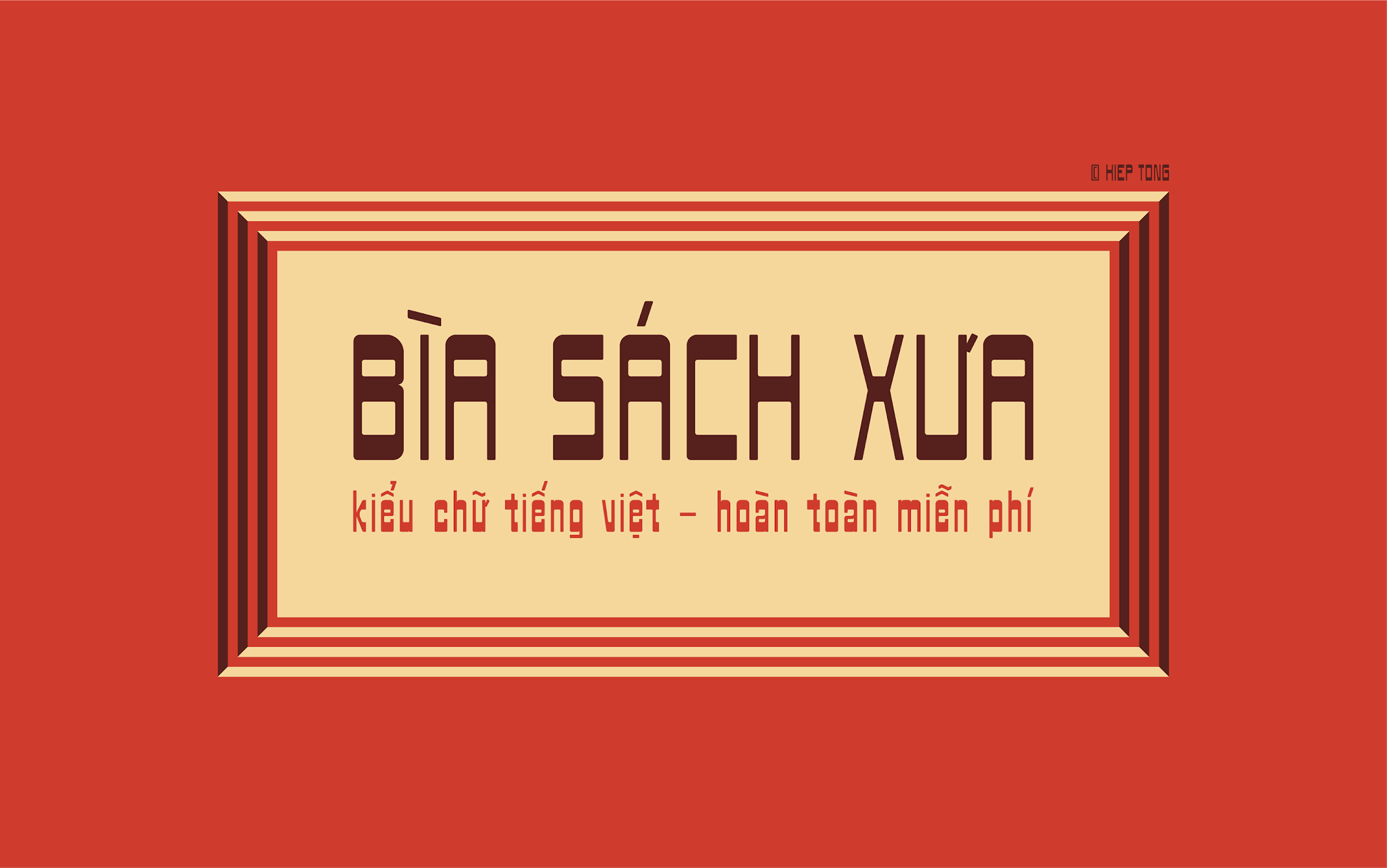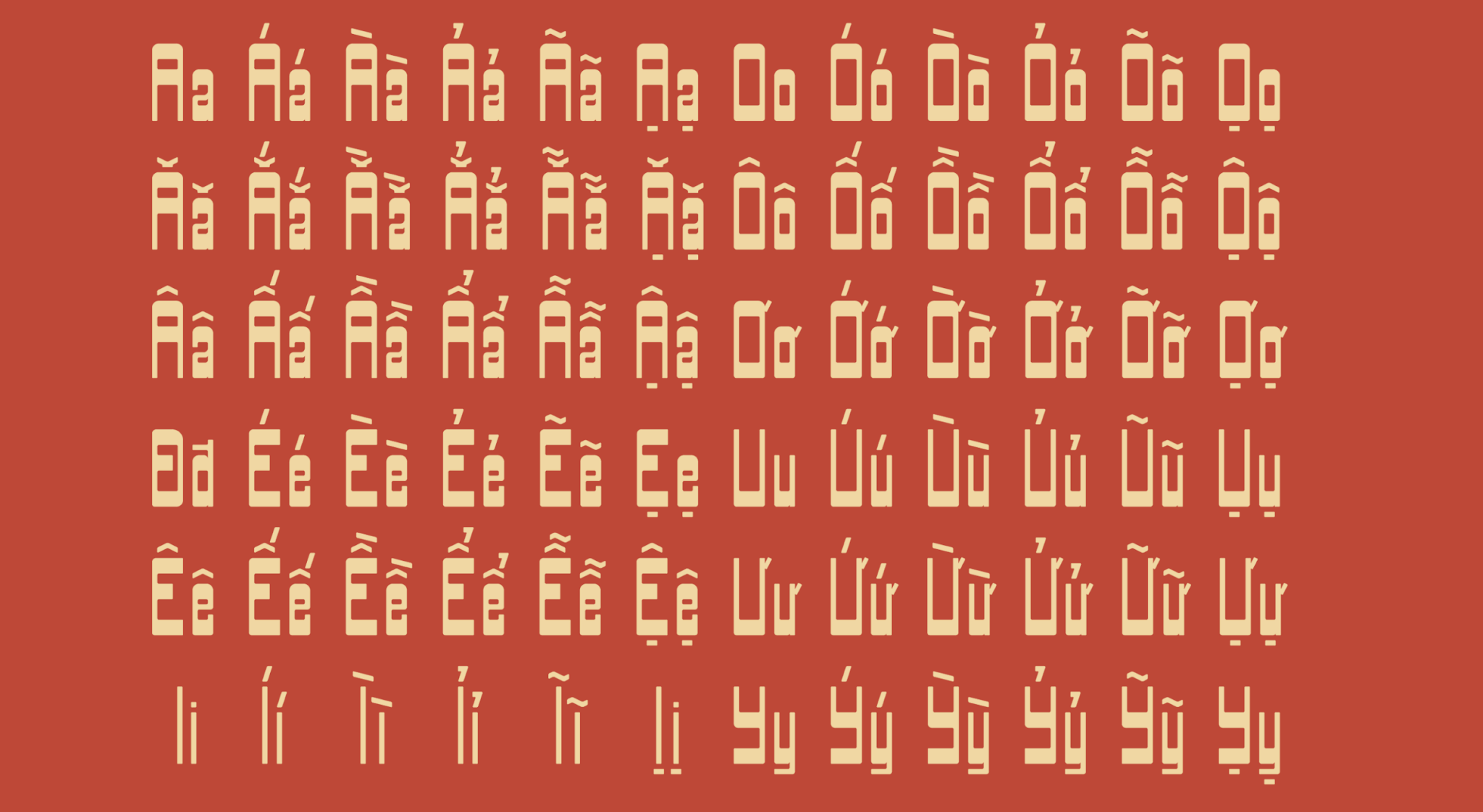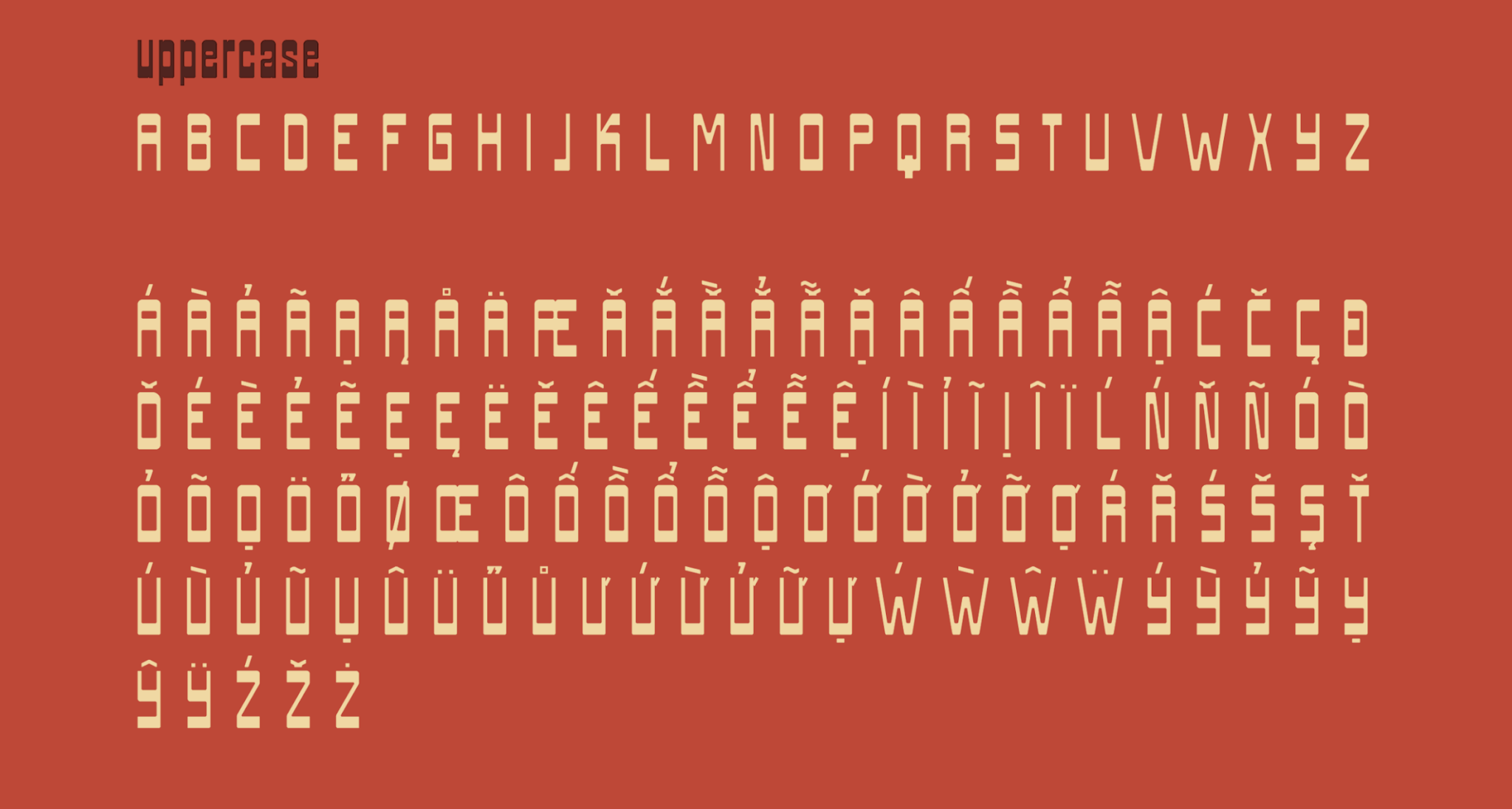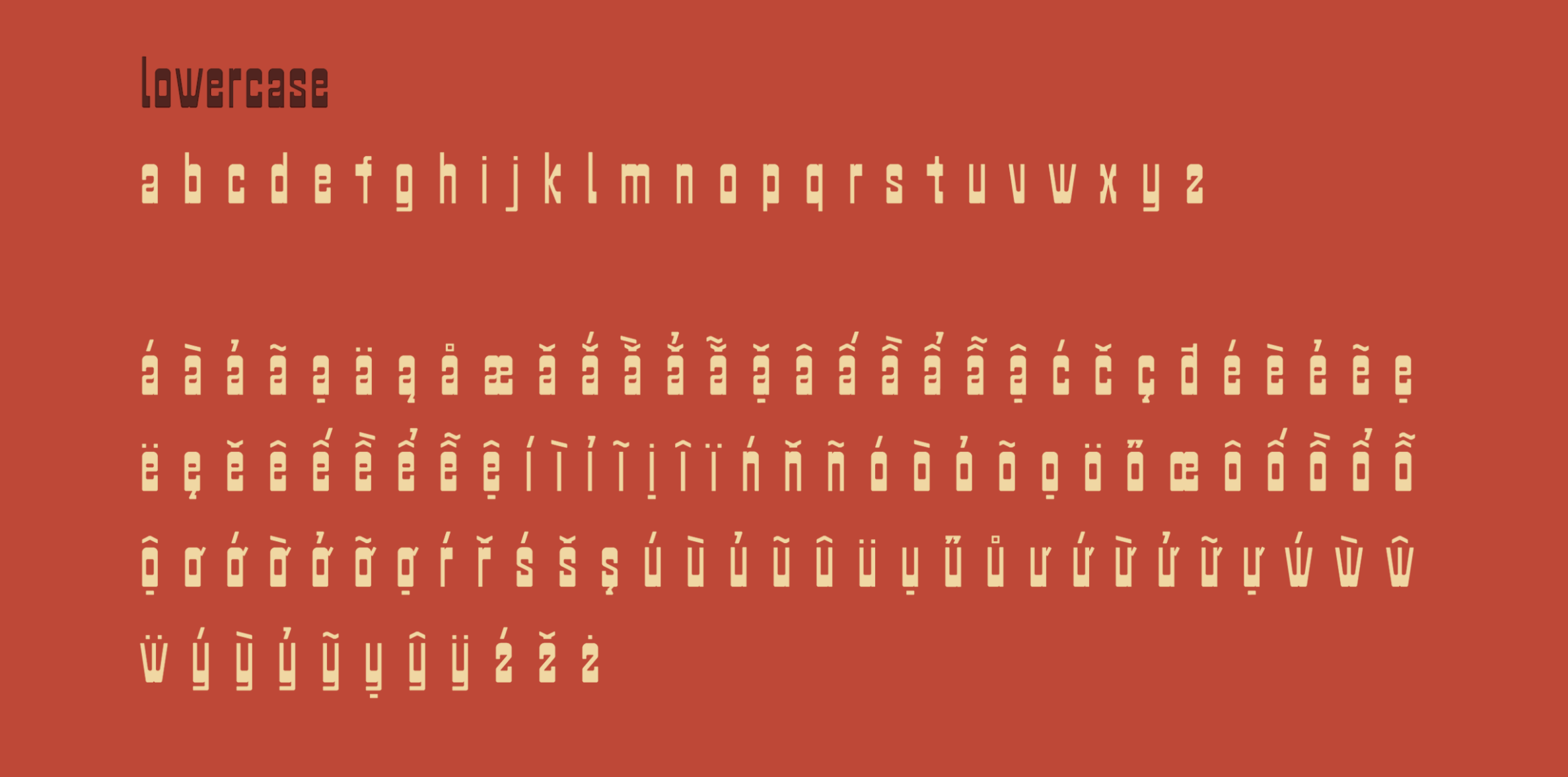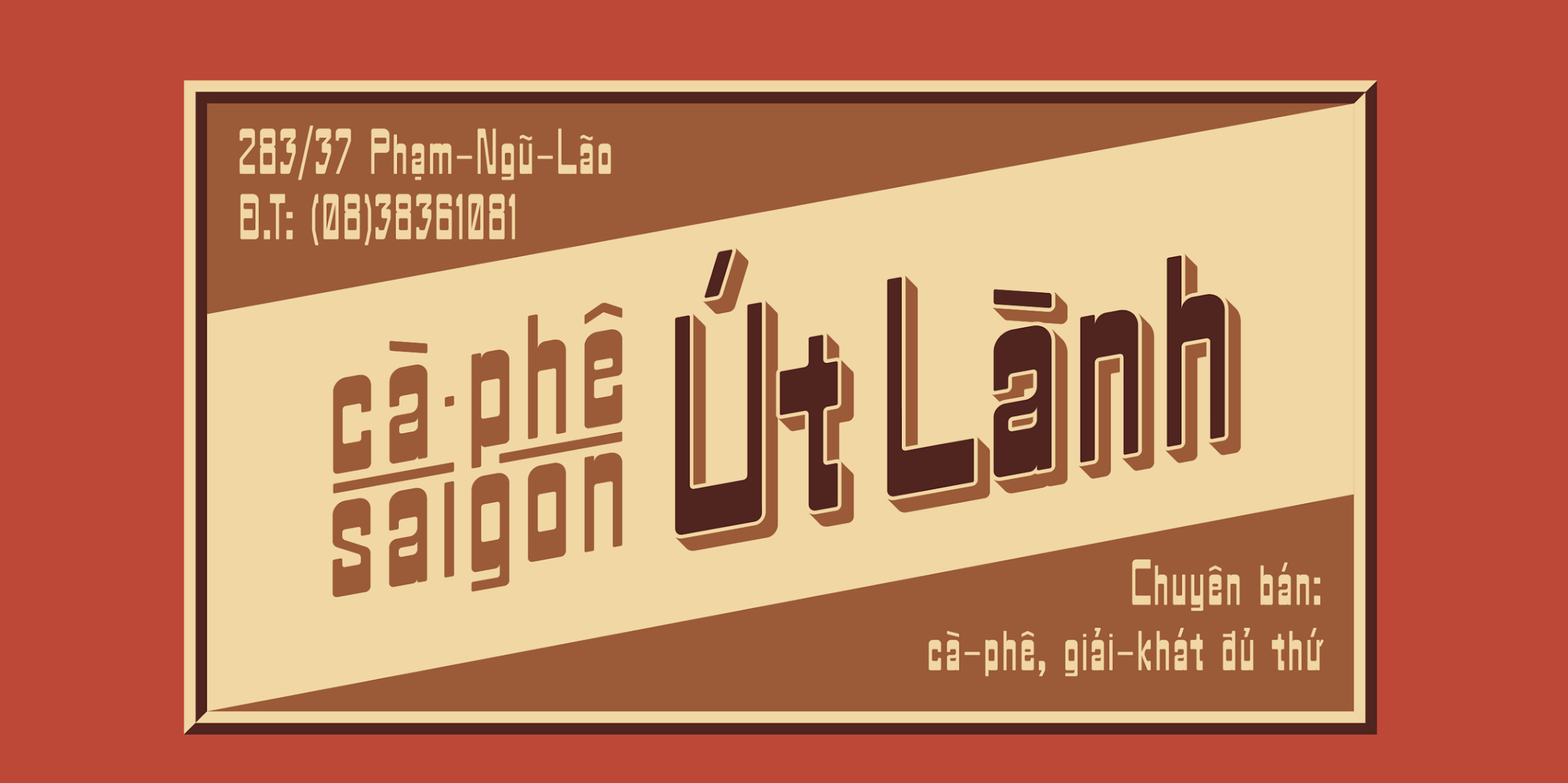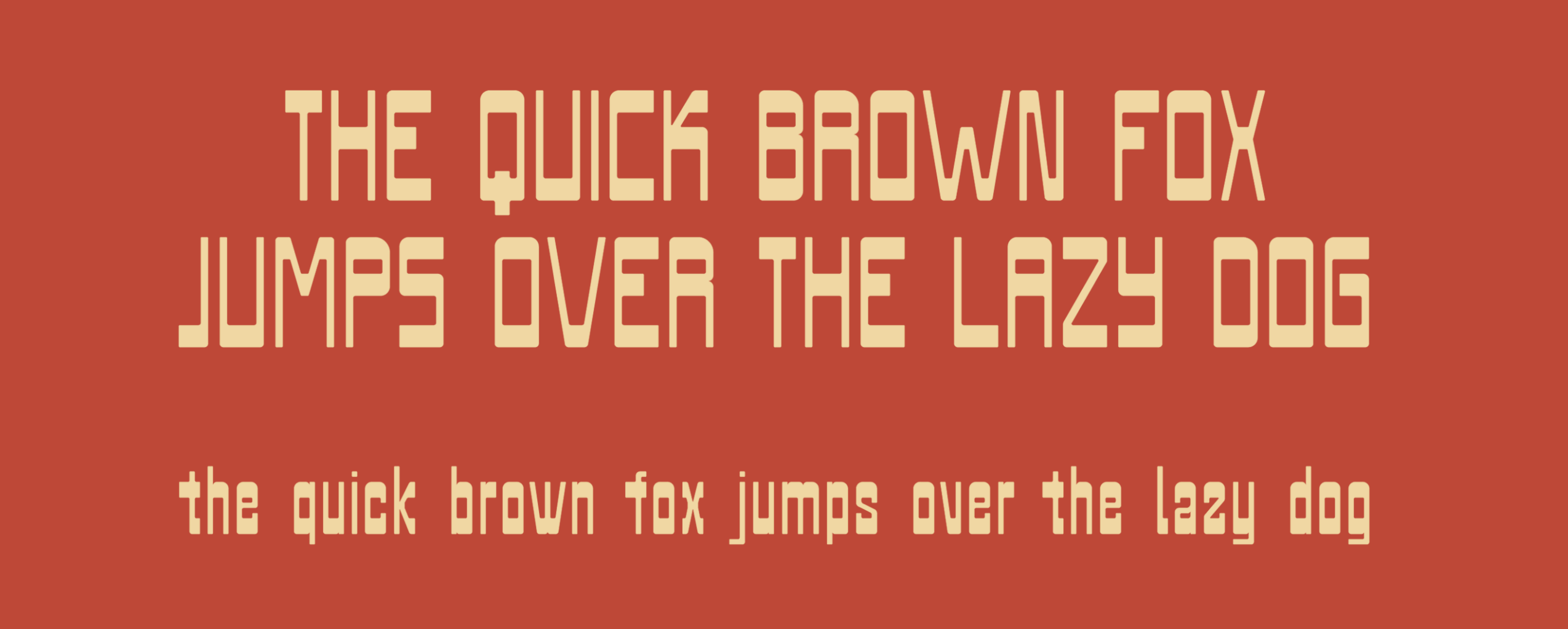
Font Biasachxua – Font chữ thời bao cấp
Font Biasachxua có nghĩa là “Sách xưa” được thiết bởi Hiep Tong. Biasachxua typeface hỗ trợ tiếng Việt và nhiều ngôn ngữ khác. Font chữ được tác giả lấy cảm hứng từ những bìa sách cũ những năm 80.